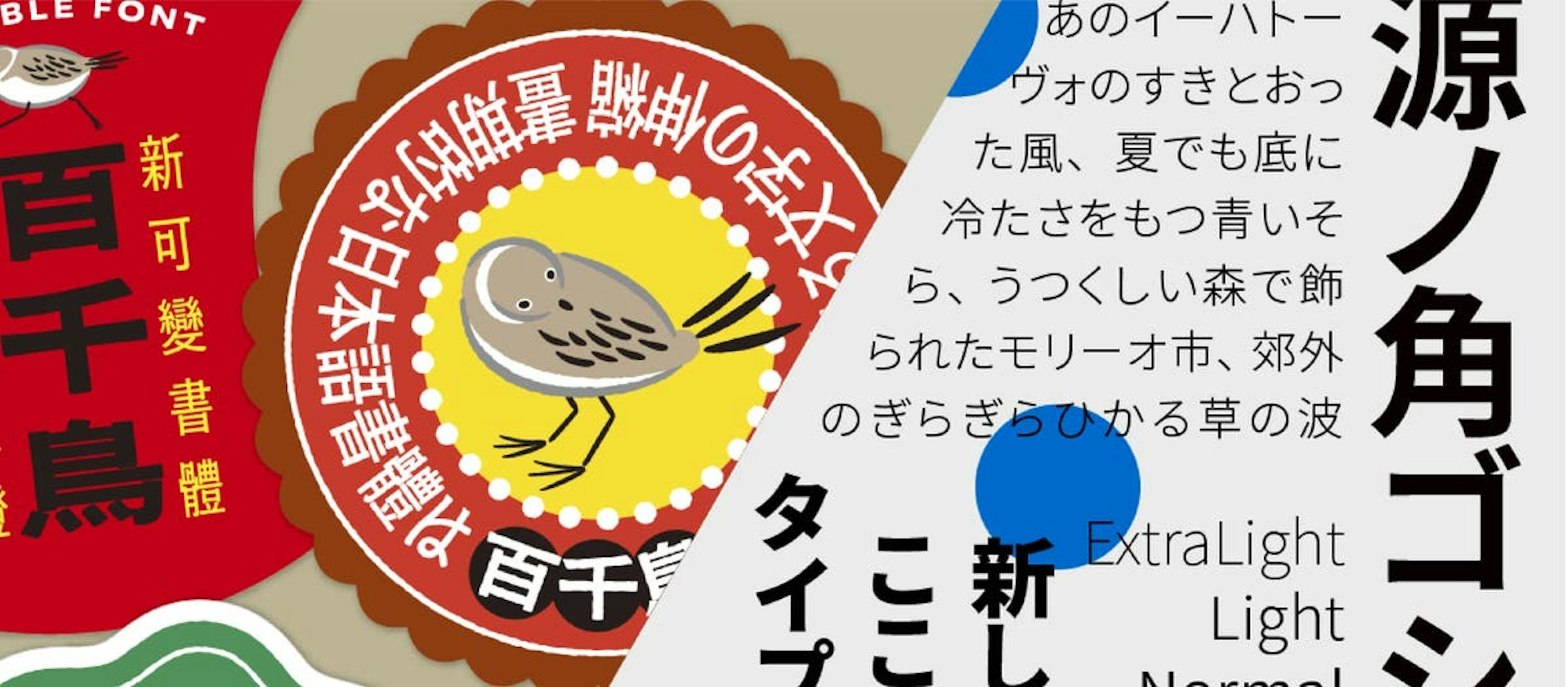
Adobe Fonts:百千鳥と源ノ角ゴシックの機能向上、新欧文フォントChidoriをリリース
Adobeは、Adobe Fontsの人気フォント「百千鳥」と「源ノ角ゴシック」の大幅なアップデートを実施し、併せて新しい欧文フォント「Chidori」をAdobe Originalsからリリースしたと発表した。これらのアップデートにより、日本語フォントの文字組みがより美しく改善され、デザイナーの表現力がさらに拡充される。
百千鳥フォントでは、拗音・促音(ちゃ、ちゅ、ちょ、っなど)の小書き文字の表示位置が見直され、文中でより適切なポジションに調整された。また、「メ」の2画目の形状調整と「を」のパスエラー修正により、より精密な文字デザインを実現している。一方、源ノ角ゴシックはUnicode URO and Extension Aに完全対応し、25の新しい文字コードに対応。さらにUnicode Version 16.0で追加された8つの標準化されたバリエーション配列(SVSes)にも対応した。
新たにリリースされた欧文フォント「Chidori」は、百千鳥フォントとの共同プロジェクトから生まれたバリアブルフォントだ。日本語との混植を前提としない設計により、太さや字幅のバリエーションをより広くカバーし、書体本来のダイナミックで精巧なデザインを活かすことができる。RomanとItalicの2スタイルで、各スタイルには30種類のプリセットインスタンスが用意されている。